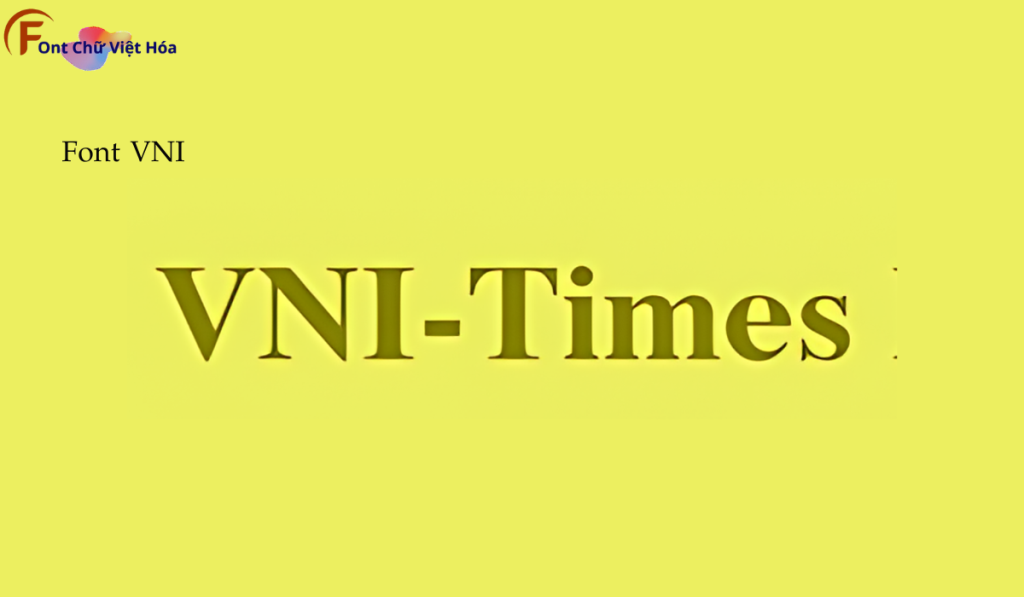
Font VNI Times Việt Hóa
Bộ Font: Font VNI
Phân loại: cá tính
Kiểu chữ: có chân
Độ dày: normal, bold
Font VNI Times Việt Hóa, thuộc bộ font VNI, mang phong cách cổ điển và sang trọng, phù hợp cho các dự án thiết kế như thiệp mời, bìa sách, và tài liệu văn phòng. Với các nét chữ có chân và độ dày đa dạng, Font VNI Times Việt Hóa không chỉ dễ đọc mà còn tạo cảm giác lịch lãm và chuyên nghiệp. Việc Việt hóa font giúp người dùng dễ dàng tích hợp vào các thiết kế tiếng Việt, mang lại sự tiện lợi và nâng cao tính thẩm mỹ.